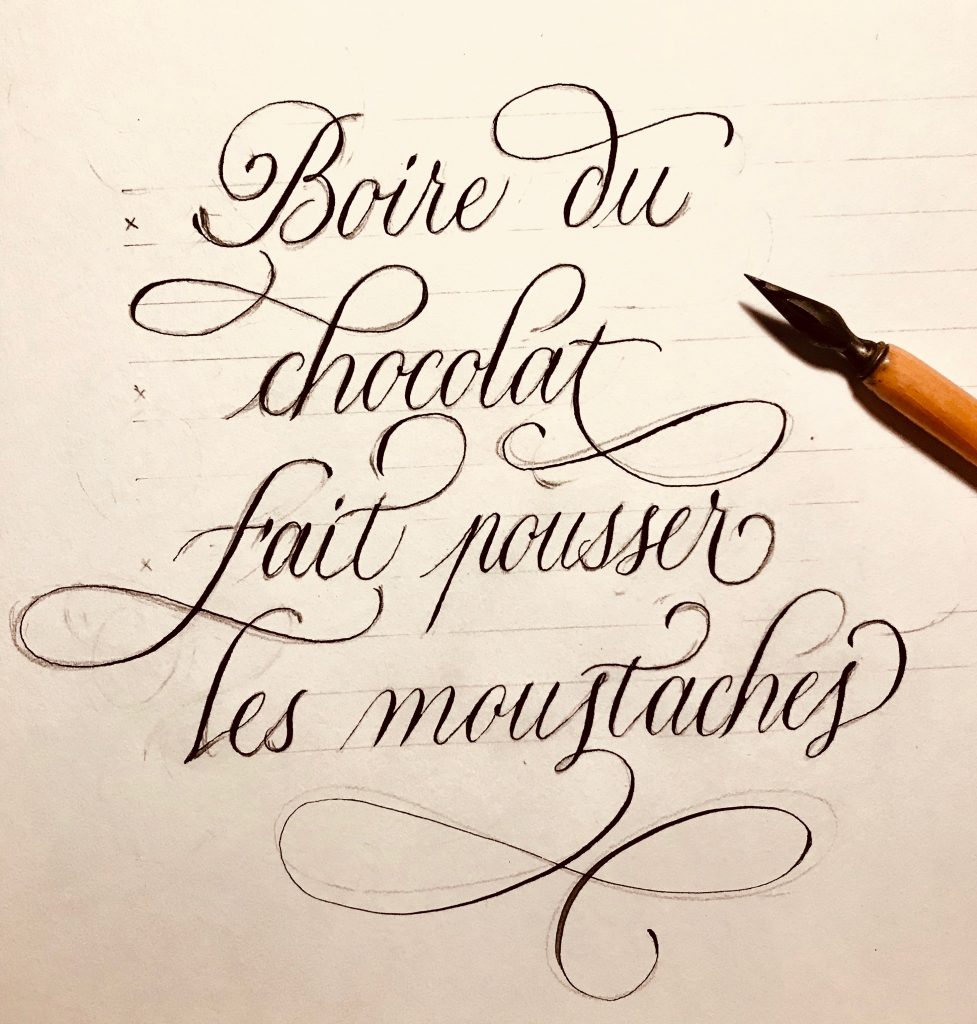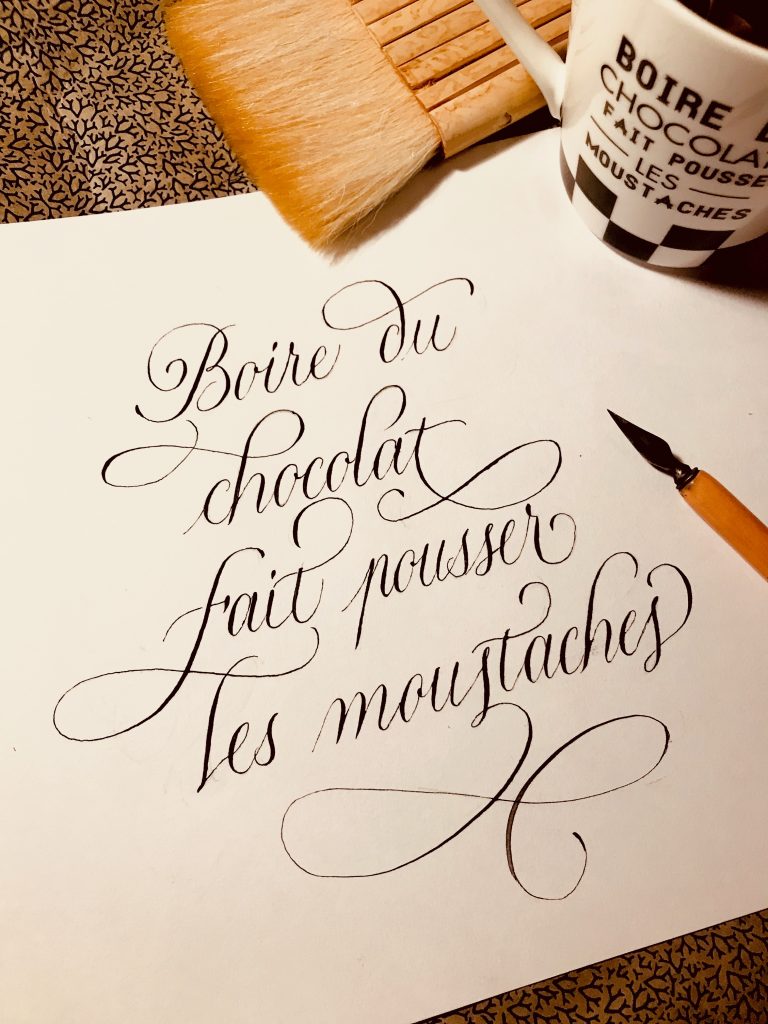
Je reprends la plume en ce mois de septembre, et vous propose de parcourir les étapes de réalisation d’un court texte avec des arabesques. Travailler les arabesques avec l’Anglaise n’est pas simple : il y a plusieurs façons de procéder, plusieurs façons de réaliser le geste selon le degré de maîtrise. Ci-dessous, j’adopte une approche « débutant » consistant à réaliser le travail d’abord au crayon de papier, puis à la plume. Les arabesques sont dessinées puis tracées avec lenteur.
Préparation
Pour la préparation, rien de bien méchant. Il faut se munir :
- d’une feuille de papier ordinaire
- d’une règle/équerre
- d »un crayon de papier et d’une gomme
Je commence par tracer une portée de 1 cm de hauteur. Si vous vous sentez plus à l’aise, vous pouvez également tracer les obliques à 54° pour mieux vous repérer. Si vous travaillez l’anglaise depuis un certain temps avec des modèles américains, vous avez remarqué que je ne respecte pas ici les proportions généralement admises pour la portée (ascendantes et descendantes plus hautes). C’est un parti pris ici.
Le fait de travailler sur 1cm de hauteur pour le corps de la lettre est une bonne approche lorsqu’on débute : cela permet de bien étirer les ovales et d’avoir une écriture plus légère (vs plus ramassée sur une portée plus petite)
Je trace une petite croix sur les lignes de base de l’écriture, toujours pour mieux me repérer. Essayez d’être léger.e en traçant la portée, afin de ne pas trop marquer le papier.
2. Ecrire le texte en anglaise simple, au crayon de papier
Le texte est rédigé une première fois, sans fioritures (si ce n’est la majuscule), au crayon de papier. Les pleins et les déliés ne sont pas appuyés. L’objectif est ici de dresser la disposition globale du texte et de veiller à un interlettrage équilibré. Vous pouvez retoucher le texte afin qu’il soit correctement ancré (à droite, à gauche ou centré). Ici, je l’ai plutôt centré.
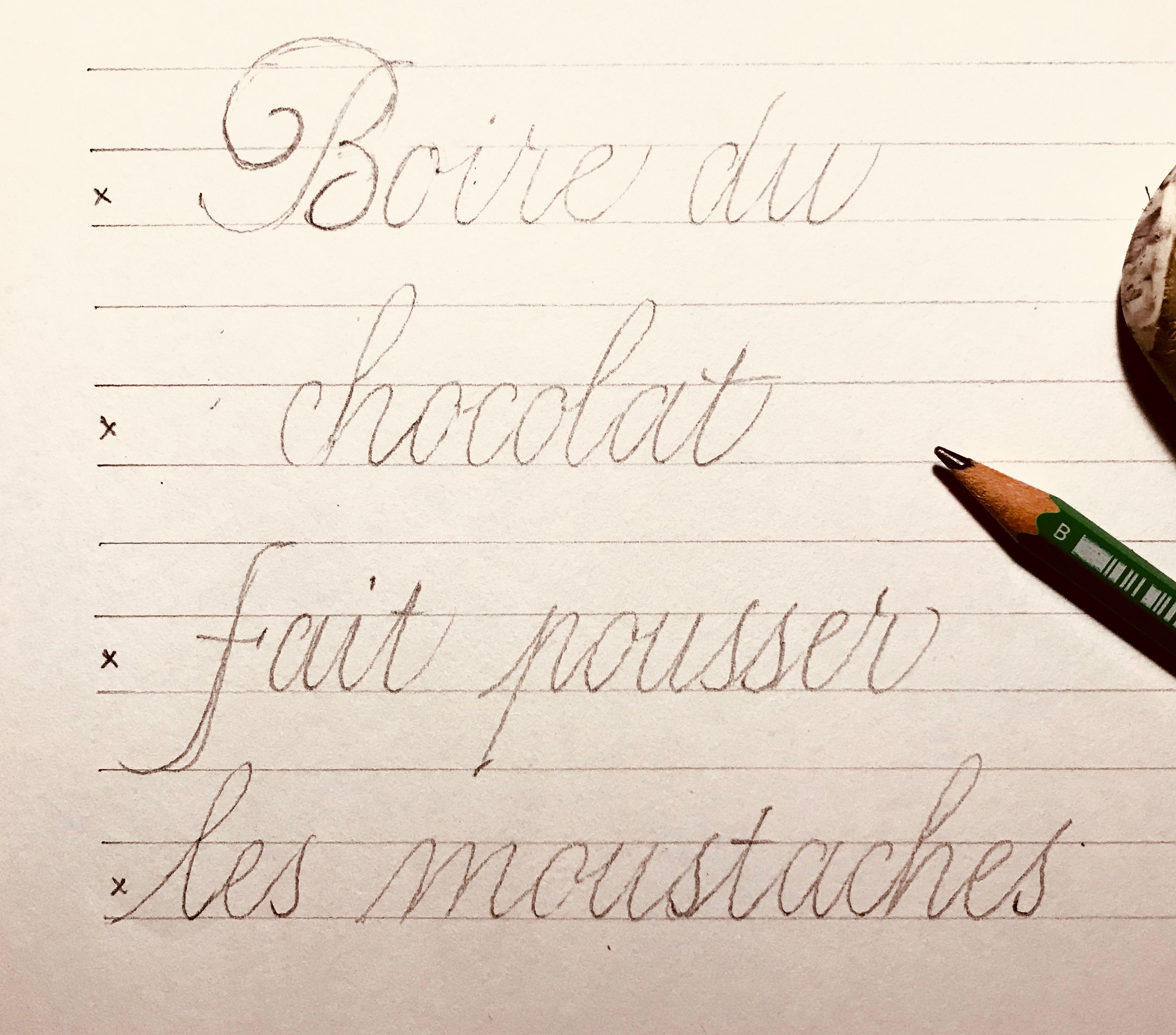
3. Réaliser les arabesques, premier jet
Une fois le texte bien disposé, je m’arme d’une gomme et je démarre le travail sur les arabesques. Celles-ci peuvent être réalisées par exemple :
- Sur les lettres ascendantes (b, l, k…) pour le donner un côté aérien, vers le haut
- Sur les lettres descendantes (g, q, p…)
- En fin de mot
Je m’attaque donc aux ascendantes, et commence à étirer les lettres et à former les arabesques. Le travail se fait progressivement, mais il n’est pas obligatoire de commencer par le début du texte.
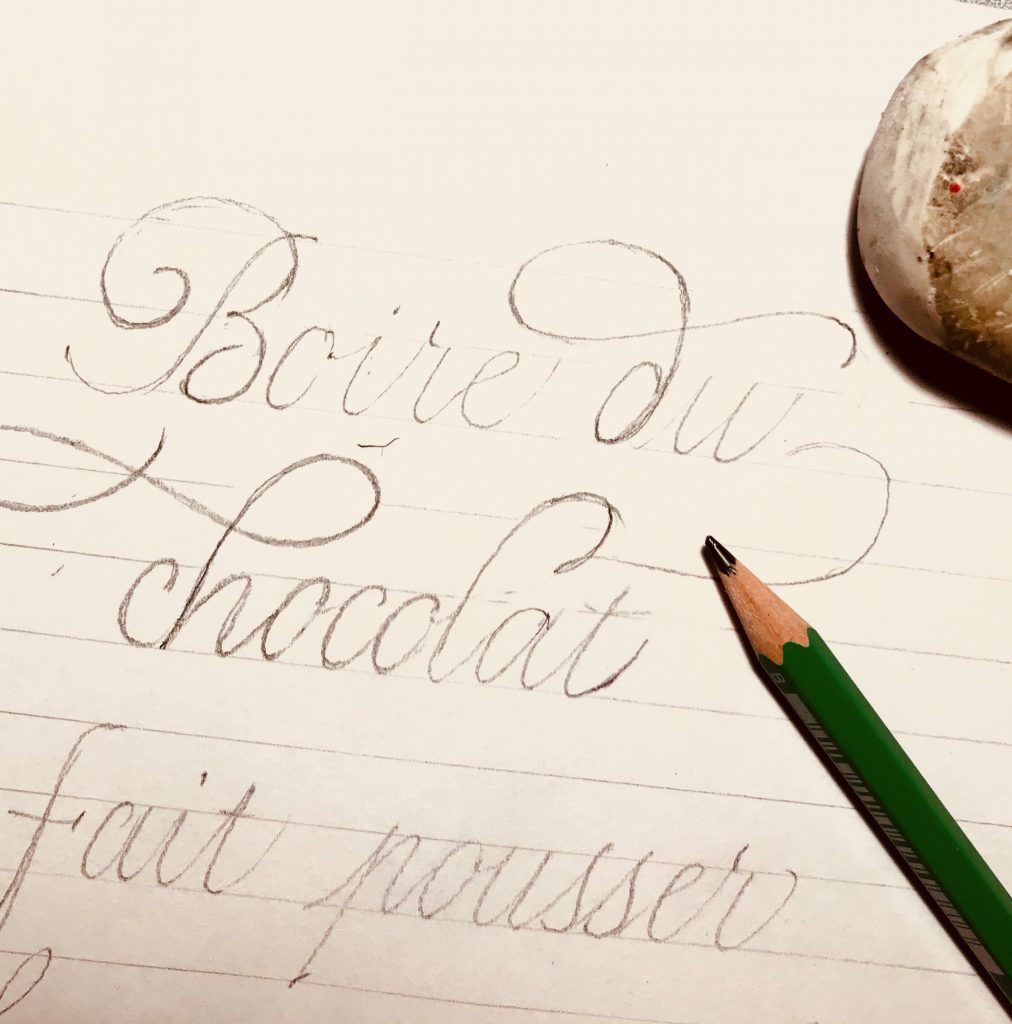
On peut essayer de créer des liaisons entre les mots d’uhne ligne à l’autre, comme ici la ligature entre le S et la barre du T de la ligne inférieure.
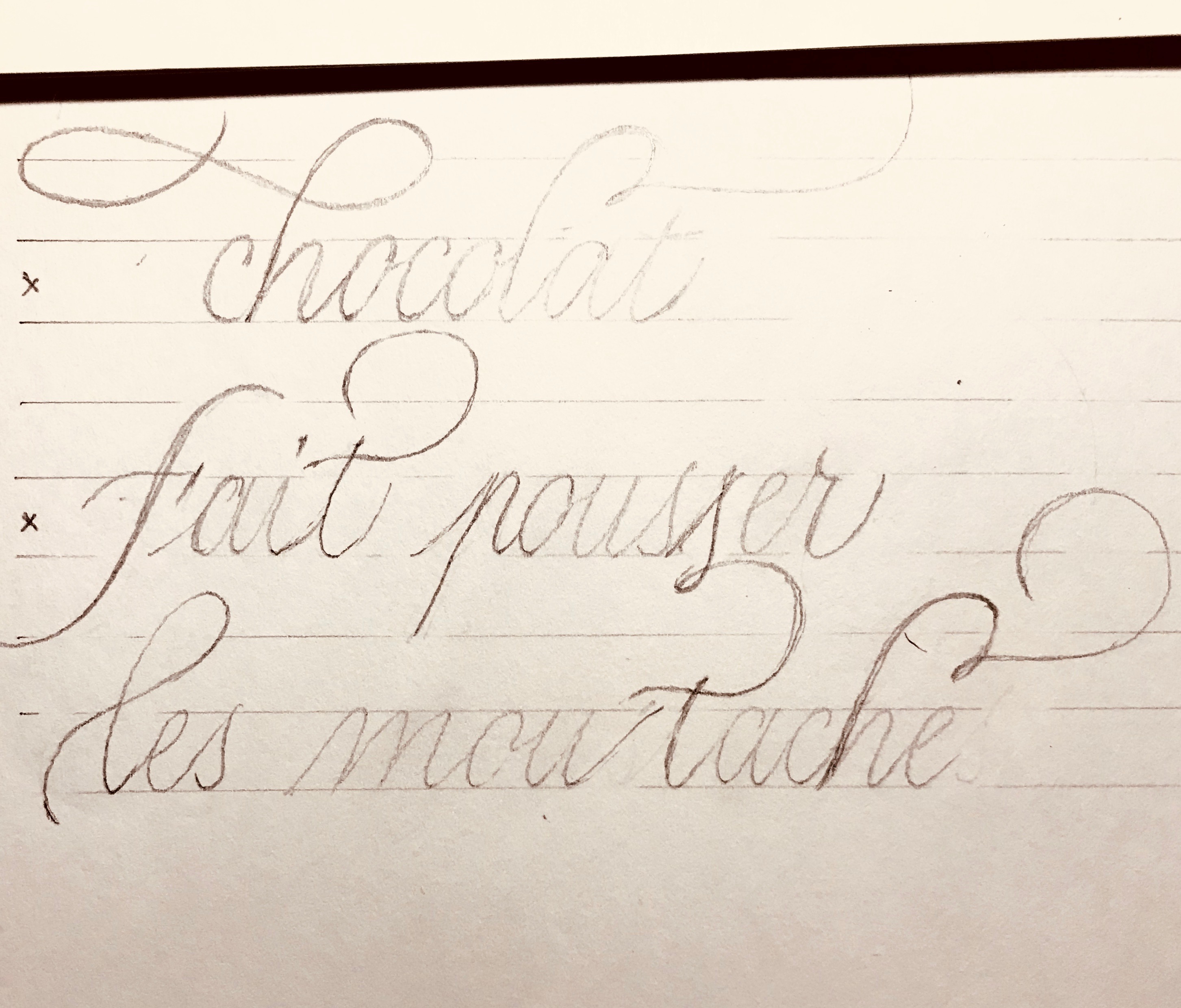
Ci-dessous une première version du texte complet : les arabesques sont plutôt pas mal, mais vous remarquez comme moi que l’ensemble n’est pas équilibré :
- tout le poids semble porter à droite : le côté gauche semble un peu vide
- je trouve que c’est un peu too much : trop d’arabesques tuent l’arabesque
Donc je reprends gomme et crayon pour rééquilibrer la composition.
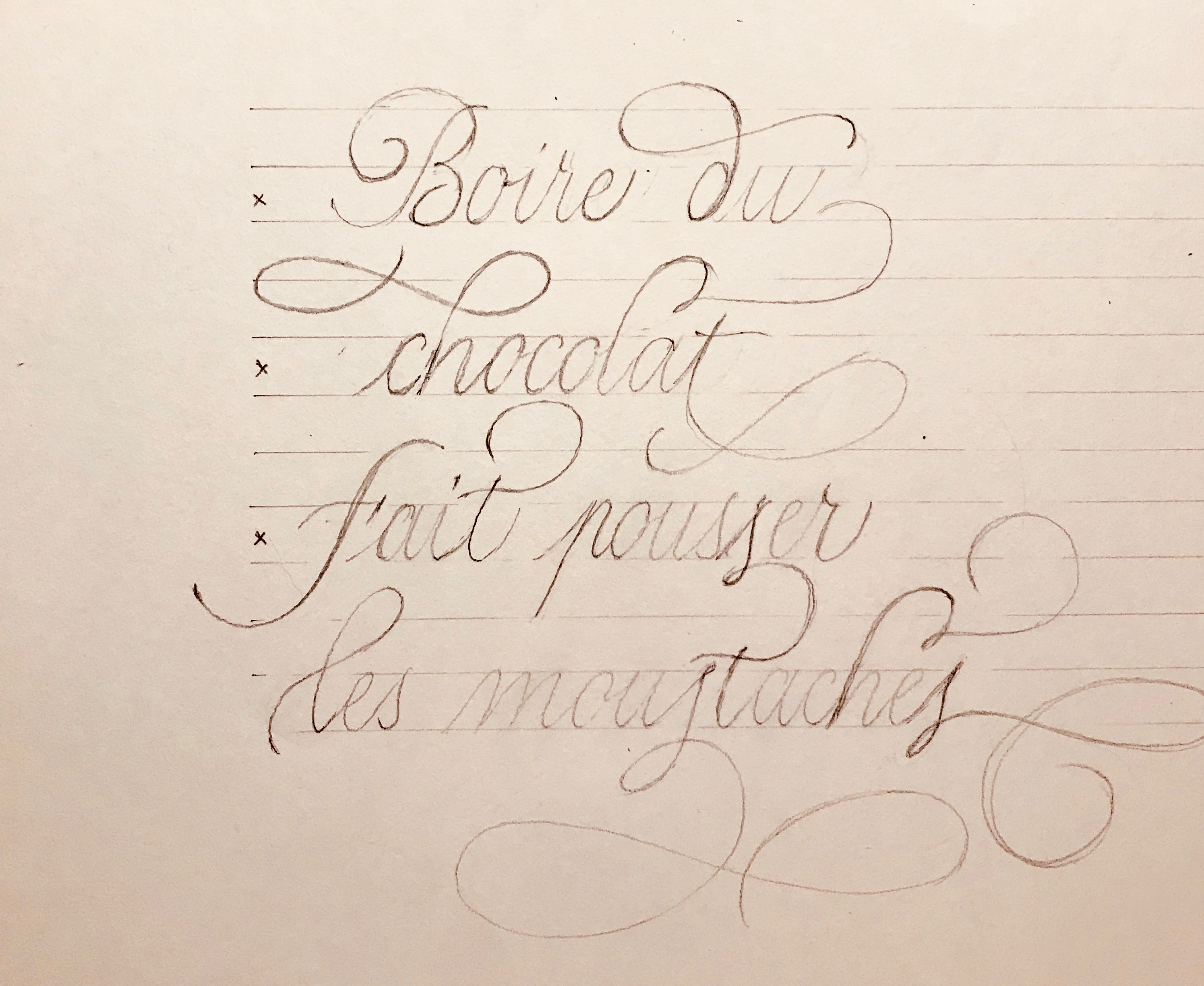
4. Réaliser les arabesques, second jet
J’ai gommé une grande partie du travail réalisé dans le premier jet, pour arriver à une seconde version qui me paraît plus équilibrée :
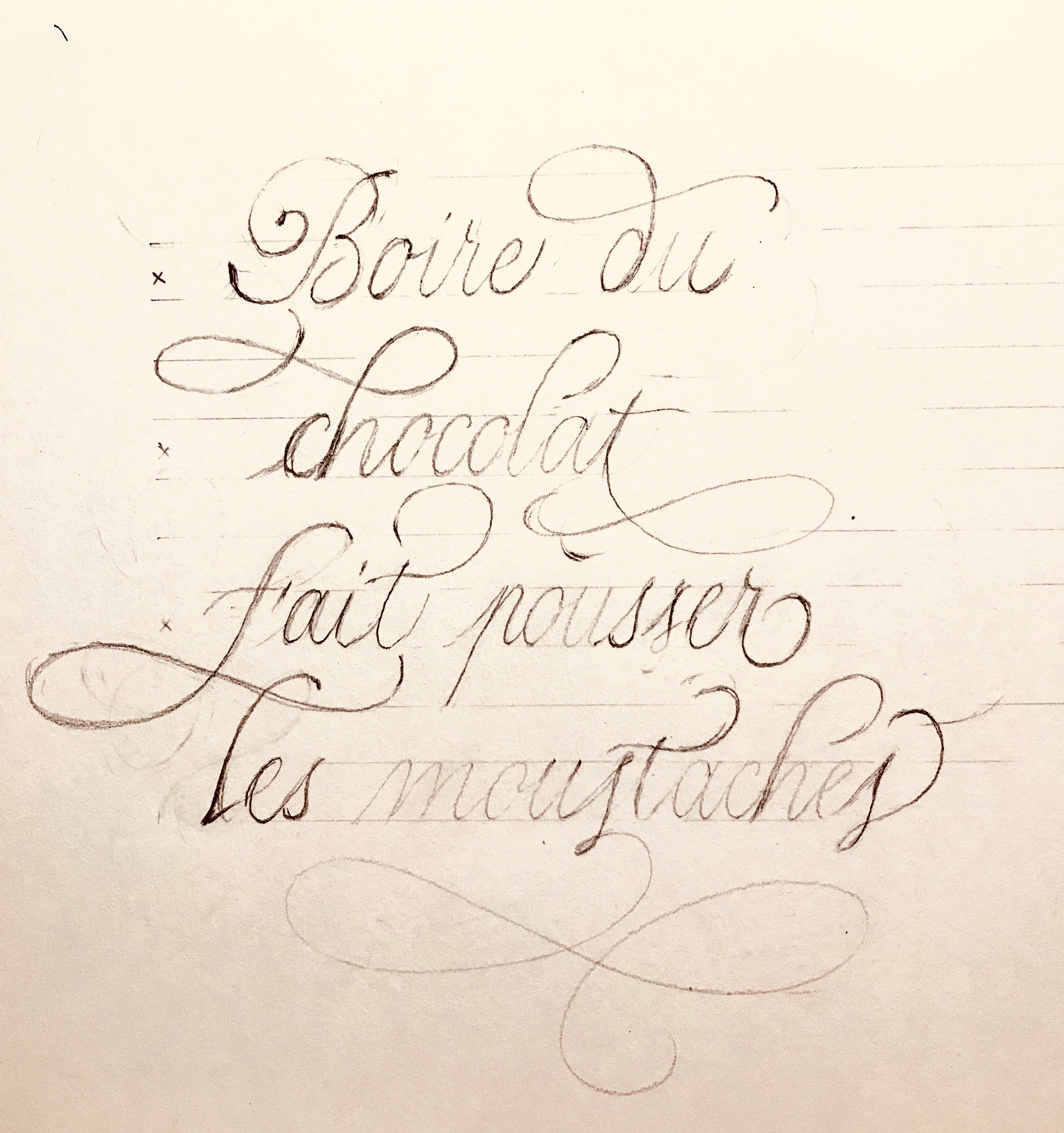
- Finalement la ligature entre le S de « pousser » et la barre du T de « moustaches » a été sacrifiée
- Etirer le trait descendant du F permet de repartir un peu vers la gauche. Afin de ne pas trop superposer les boucles, j’ai dû retoucher le L de « les », en lui conservant une forme ouverte, plus aérienne qu’un L bouclé et fermé.
- Le S final de « moustaches » a été simplifié, tout en conservant une sortie élégante
- Le L de « chocolat » a lui aussi été simplifié, car je trouvais que c’était trop et que cela cassait l’équilibre.
Comme vous le voyez sur la photo ci-dessus, les reprises ont été nombreuses.
5. Encrer le texte
Une fois la composition satisfaisante, on peut passer à la phase d’encrage à la plume. J’ai gommé légèrement tout le texte et les traits de base pour ne conserver que le trait de surface. On peut aussi décalquer le texte ou le recopier au propre, et au crayon, sur une nouvelle feuille de papier.
J’ai ensuite pris une plume pointue, de l’encre, et c’est parti :
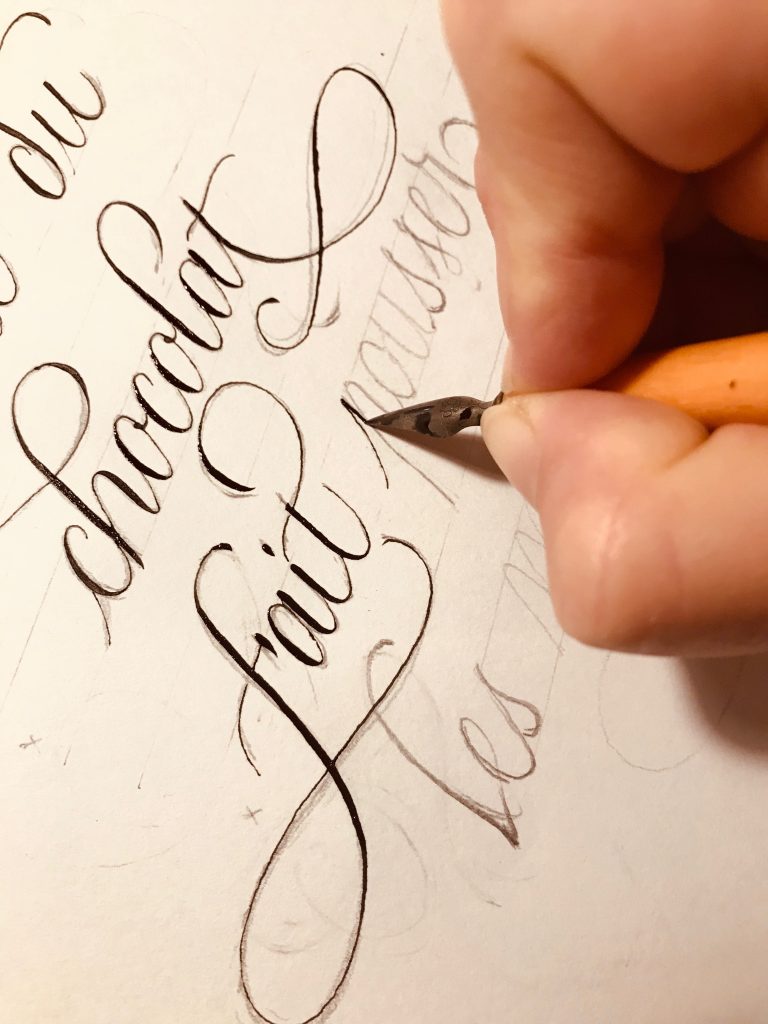
Le tracé est effectué avec lenteur. Pour les grandes boucles, je m’efforce de tracer à main levée . Ce n’est pas évident car on a tendance à garder un appui sur l’avant bras, mais cela empêche d’avoir des geste amples et réguliers, car on joue alors sur la torsion du poignet pour tracer les courbes. Donc si vous le pouvez, levez le coude !
Le passage à l’encre est l’étape la plus délicate. Quelques conseils :
- N’ayez pas peur, ne vous crispez pas : même si on a parfois tendance à tracer une lettre comme si notre vie en dépendait, et bien ce n’est évidemment pas le cas, donc keep cool. Et si c’est raté, et bien ce n’est pas grave, vous pouvez recommencer.
Merci pour ce tutoriel – les arabesques présentent 2 difficultés : l’équilibre visuel du texte mais surtout lever le coude – ce que je n’arrive pas encore à faire en calligraphie…. pour trinquer c’est plus spontané !